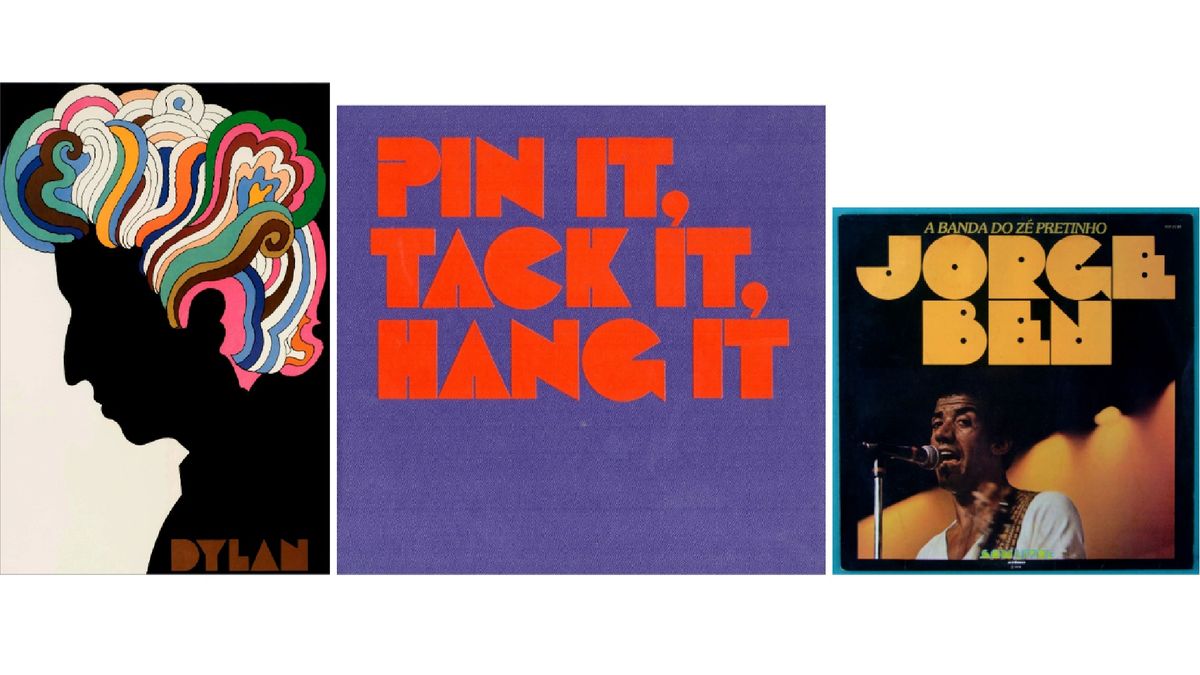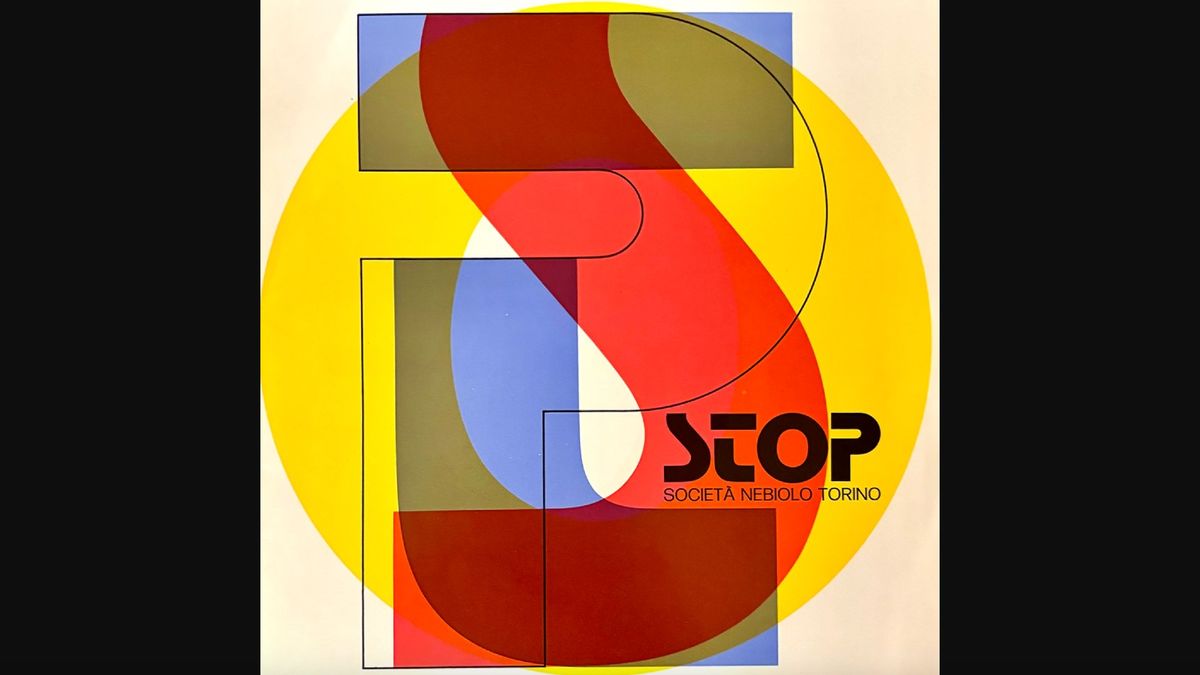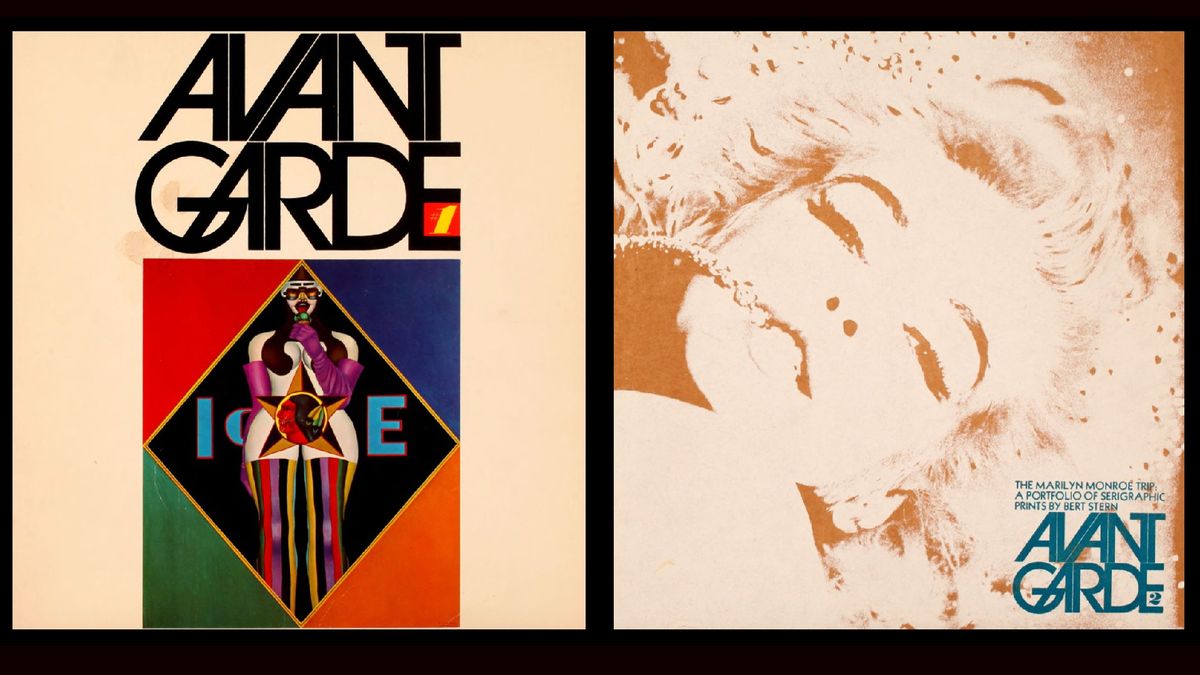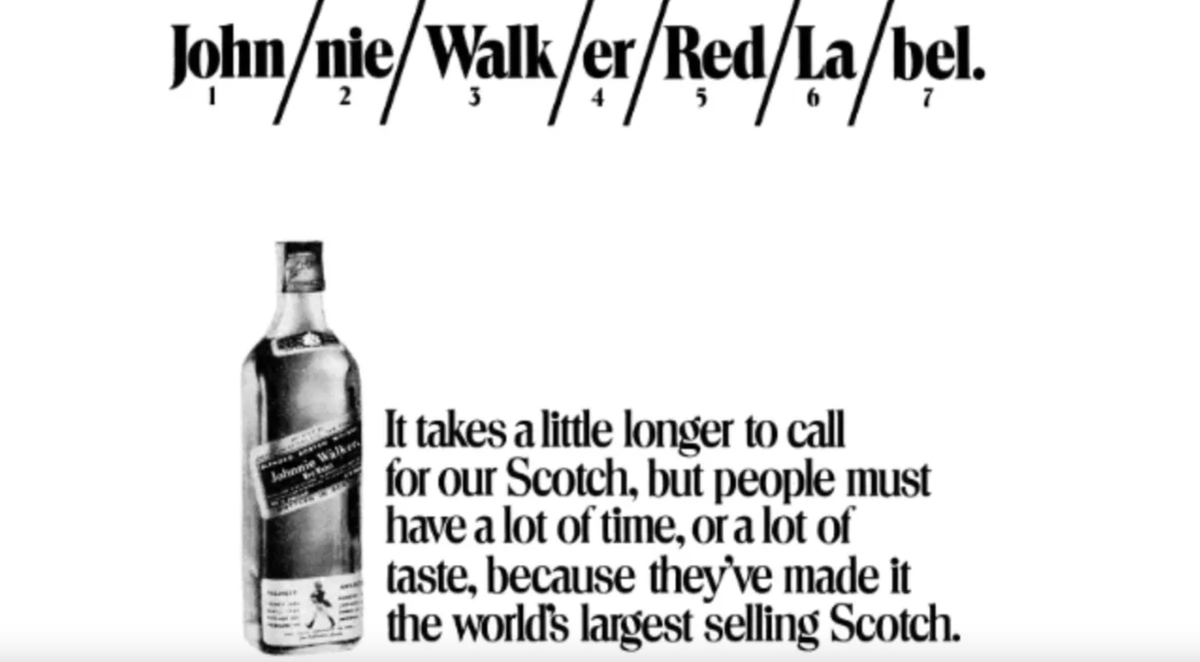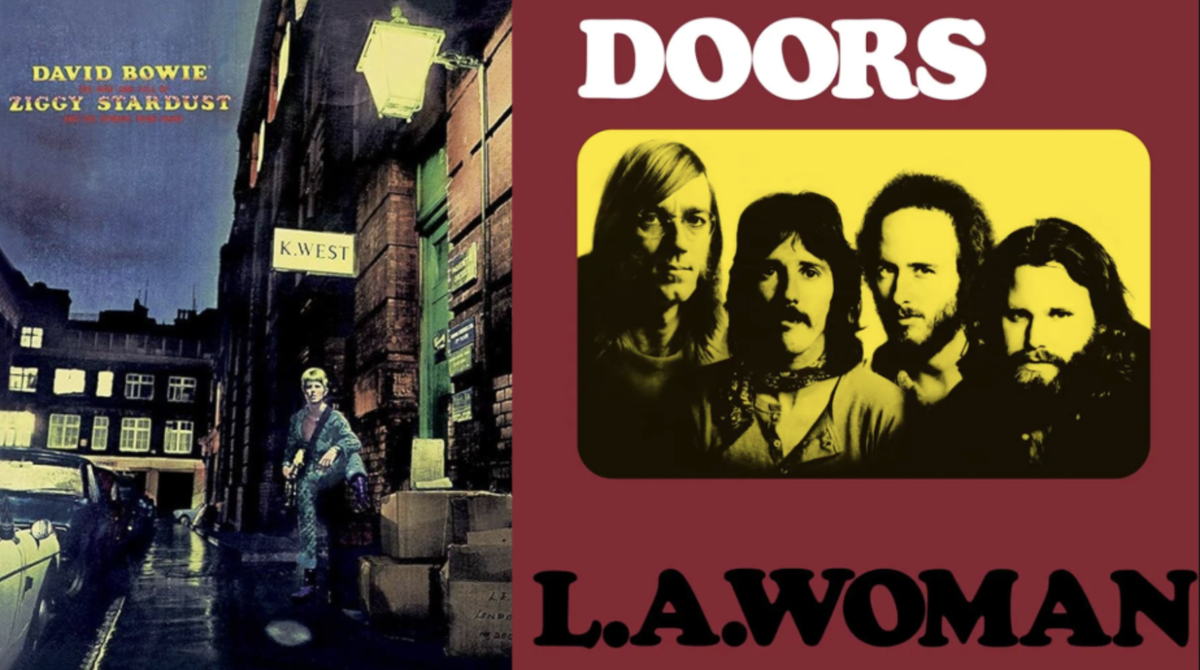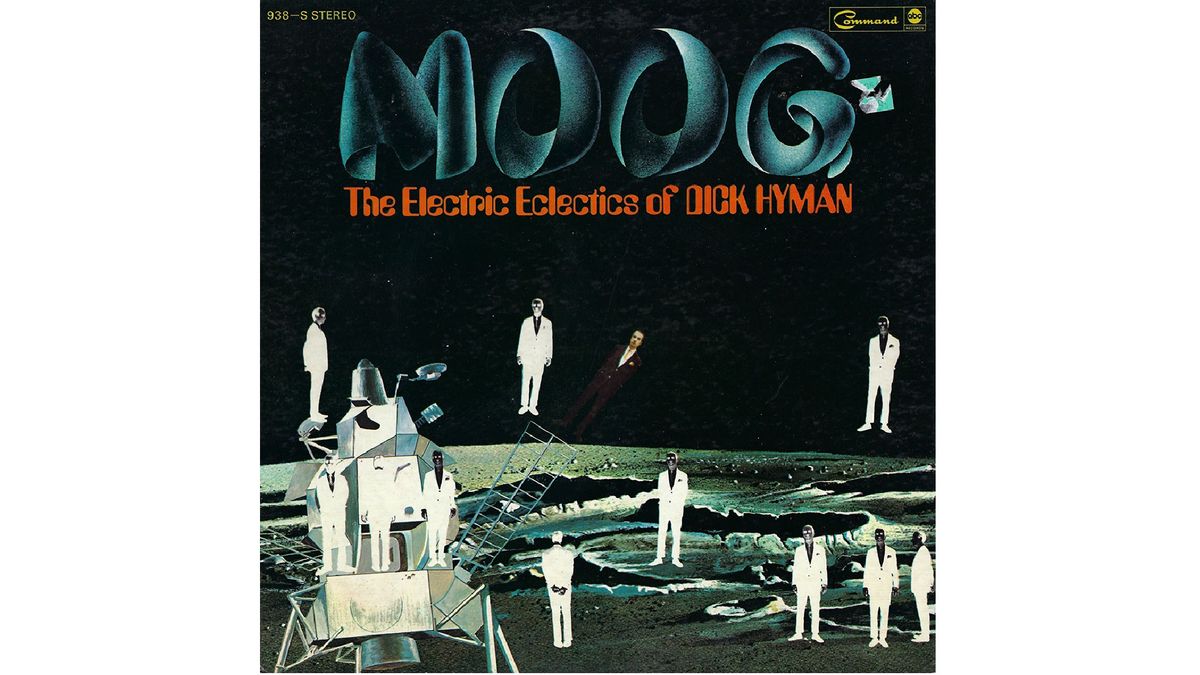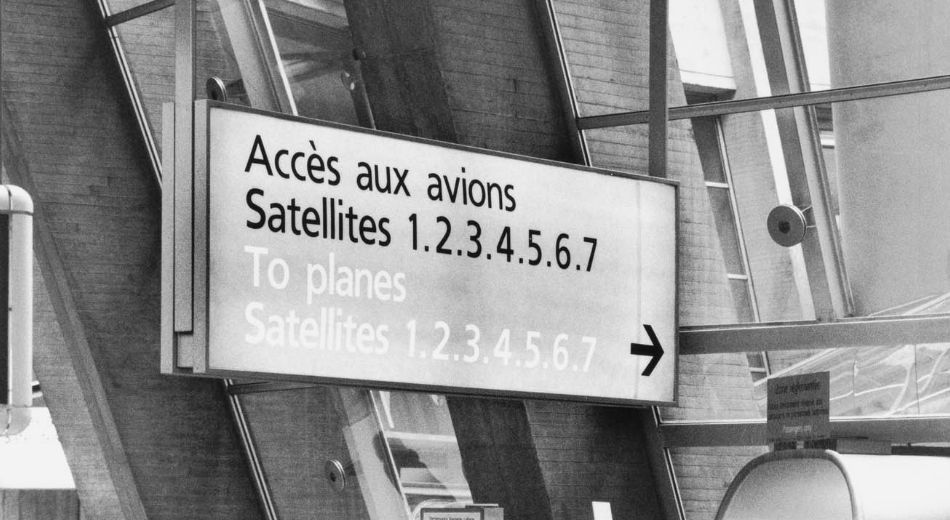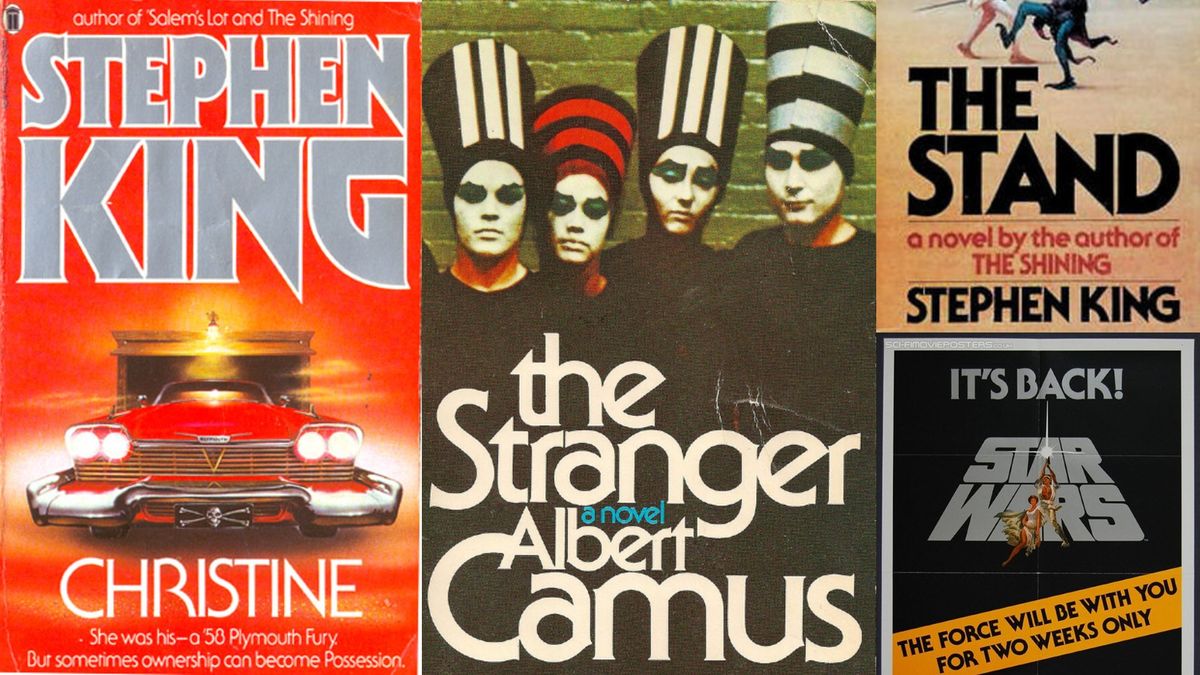
Дизайн 70-х: Как шрифты изменили искусство и пробудили креативность
Вы когда-нибудь задумывались, как типографика может изменить восприятие всего вокруг? Да-да, именно так! 70-е годы — это не просто десятилетие моды и музыки, это настоящий бум в мире дизайна. Время смелых решений, безумных экспериментов и, конечно же, невероятных шрифтов, которые оставили след в истории графического дизайна. ✔️
Эволюция шрифтов: своего рода магия
Когда в 1970-х годах дизайнеры начали покорять новые горизонты с помощью фототипографии, они словно получили сверхспособности! 🦸♂️ Шрифты больше не были привязаны к материалам и физическим ограничениям. Буквы могли переплетаться, перекрываться и взаимодействовать друг с другом, что дало новые возможности для креативности.
Мильтон Глейзер, например, создал шрифт Baby Teeth, который стал символом контркультуры. Этот рваный стиль и игривость очень эффектно отражали психоделическую эстетику своего времени. Настоящий шедевр! 🎨
А кто не слышал о шрифте Stop от Nebiolo? Его геометрические формы идеально подходят для логотипов и инициалов, он словно ведет нас в мир надежды — очень актуально в тексте сегодня! 😍
Признак минимализма: ITC Avant Garde Gothic
Скотт Мерфи решил сделать минимализм главной темой и создал ITC Avant Garde Gothic для одноименного журнала. Этот шрифт стал символом 70-х благодаря чистоте своих линий и чётким формам. Вот вам еще одна причина, чтобы прокачивать свои навыки в минимализме! #дизайн
От рекламы до искусства: Спектр применения
Не будем забывать и о Trooper Roman, который сделал фурор в рекламе Jonnie Walker — этот шрифт открыл двери для технологий фототипографии, взвыв до небес! 🥃 Или, например, Cooper Black, шрифт, который можно увидеть повсюду: от модных показов до рекламных кампаний. Такие округлые формы и утолщенные контуры словно приносят дух ностальгии. Как же он популярен!
И что вы думаете о Calypso? 🤔 Созданный Роджером Эккофоном, этот шрифт практически кричит о себе! Его необычные формы и яркое исполнение придают ему уникальности, и он точно привлечет внимание к любому проекту.
Хорошо, а что на современности?
Пройдя через все эти шрифты, нельзя не отметить образец четкости и функциональности — Frutiger. Разработанный для аэропорта Шарля де Голля, он эффективно используется в навигационных системах. Это говорит о том, что хороший шрифт — это не только красиво, но и удобно. Лично я считаю, что в этом есть что-то поистине гениальное! 💡
А известный ITC Serif Gothic стал фаворитом в мире научной фантастики. Он добавлял атмосферы к любимым фильмам и книгам 70-х. Как будто вчера это было! ❗️
Подводя итоги
70-е — это эпоха креативной свободы. Дизайнеры в то время начали понимать силу типографики. И, знаете, это не просто стиль, это — возможность. Возможность создать что-то уникальное, что-то, что может вызвать эмоции и оставаясь актуальным даже спустя десятилетия.
Как? Вы только посмотрите на сегодняшние примеры! От ярких логотипов до оригинальных рекламных кампаний, истоки их кроются в тех экспериментах, которые происходили более 50 лет назад. 💖